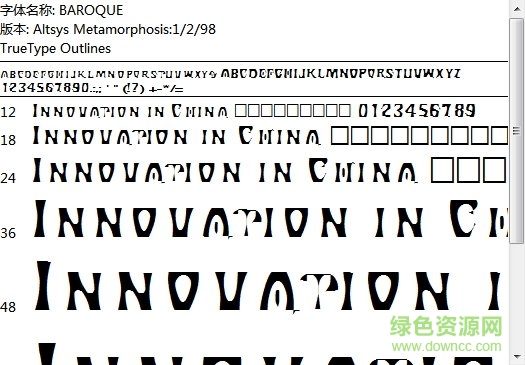
巴洛克風(fēng)格字體
巴洛克字體是一款很有baroque風(fēng)格的英文字體,風(fēng)格鮮明而迥異,給人比較出彩的英文修飾效果,是本類字體中比較杰出的一款,需要的朋友請來綠色資源網(wǎng)獲取吧!
baroque字體特色
baroque巴洛克風(fēng)格字體適用于個性美工設(shè)計,由于是英文字體,暫不支持中文使用哦,而且均是大寫英文字體格式,對你的英文內(nèi)容能起到極大的幫助和美化。
綠色資源網(wǎng)小編點評
baroque是首款以巴洛克命名的英文字體,有著比較明顯的西方字體設(shè)計風(fēng)格,給你的文字更加更多的美學(xué)體驗,適用在海報設(shè)計、包裝設(shè)計上均有著突出表現(xiàn)。